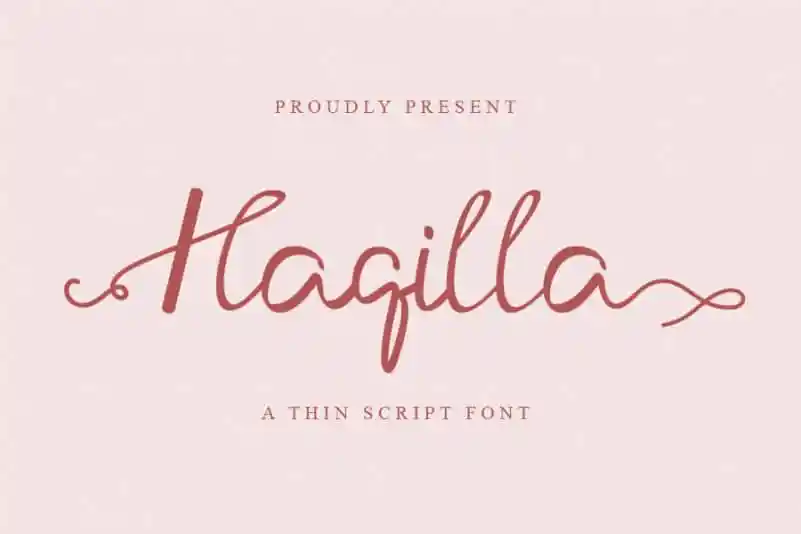
Haqilla Script Font – Download Grátis
Haqilla Script Font é uma elegante fonte escrita à mão que mantém seu charme do papel de seda ao mesmo tempo contemporânea e alegre. Suas influências clássicas de calligrafia fazem deste um recurso versátil para diversos projetos, desde cabeçalhos e assinaturas até folhettos e materiais de escritório. Seu design fluido é perfeito para aqueles criativos que desejam dar um toque único em seus projetos gráficos, garantindo assim uma combinação harmônica entre o moderno e o clássico sem perder a essência da arte do escriba. Este tipo de fonte se destaca como uma opção versátil para qualquer designer que deseja incorporar um toque especial em seus projetos.